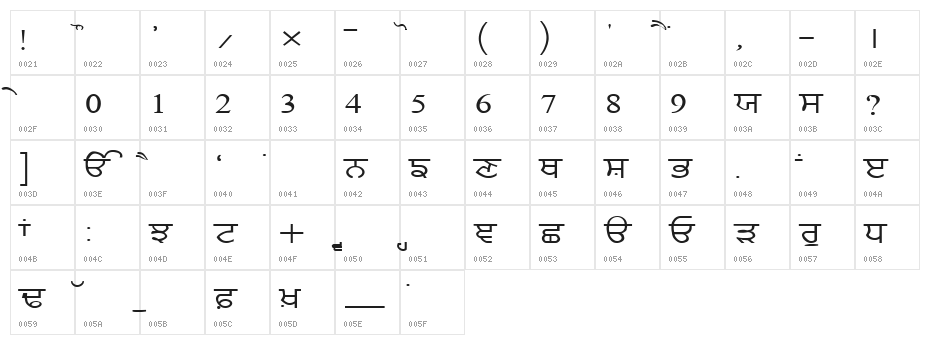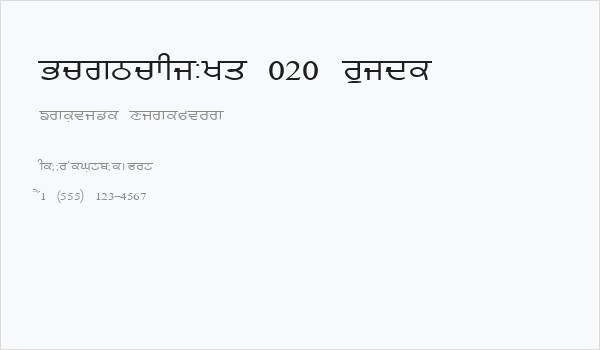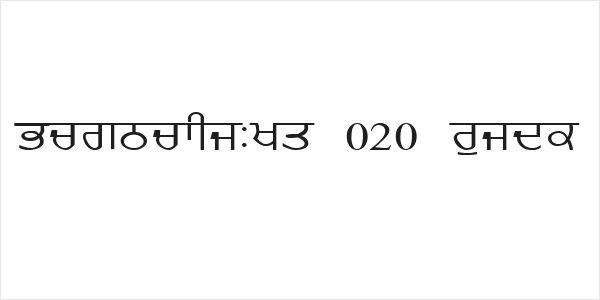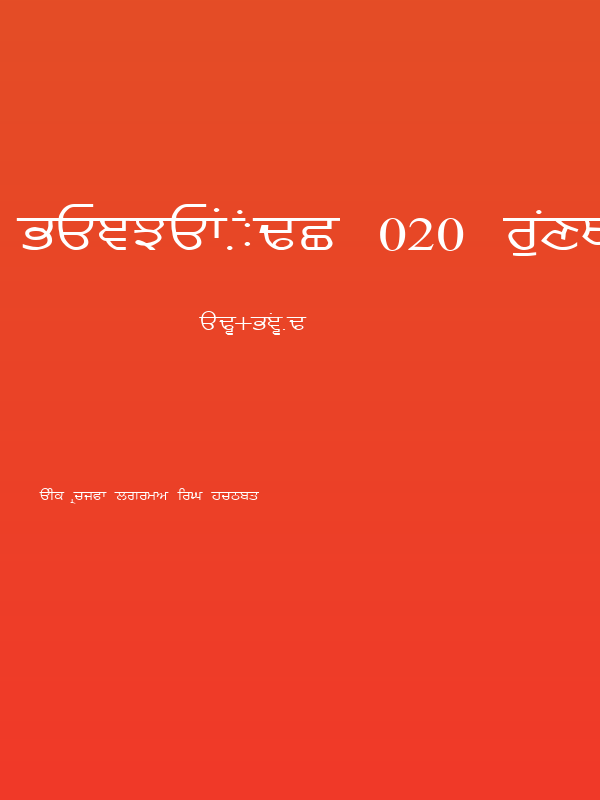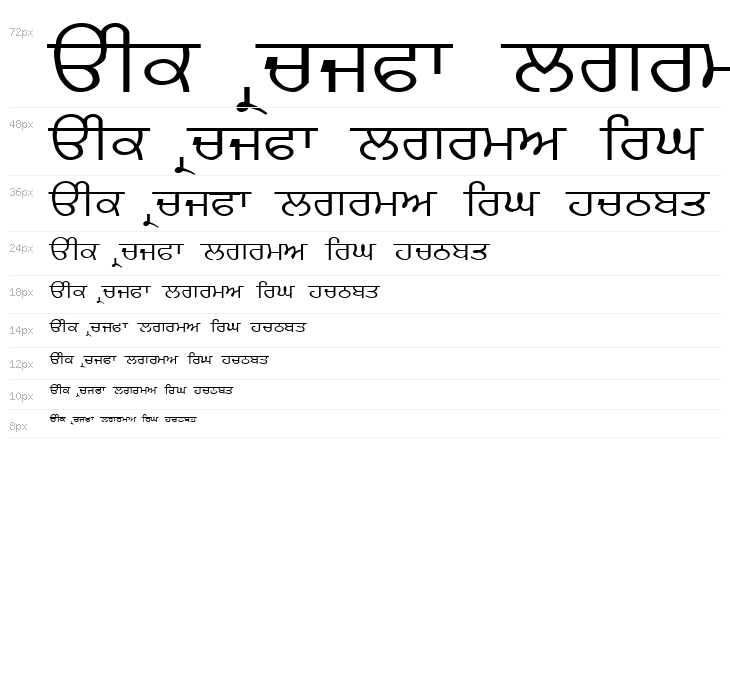
GurmukhiLys 020 Wide Font
| Caso d'uso | Body text, Educational materials, Signage |
| Progetti proposti | Ideal for educational materials, signage, digital content, and print media that require Gurmukhi script. |